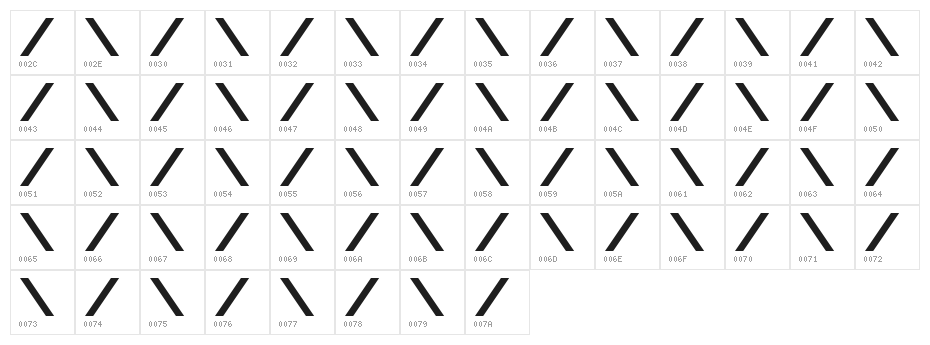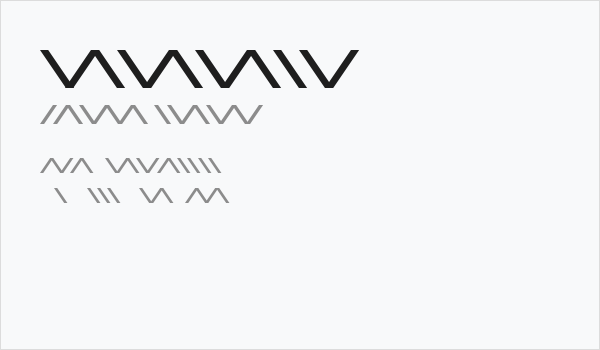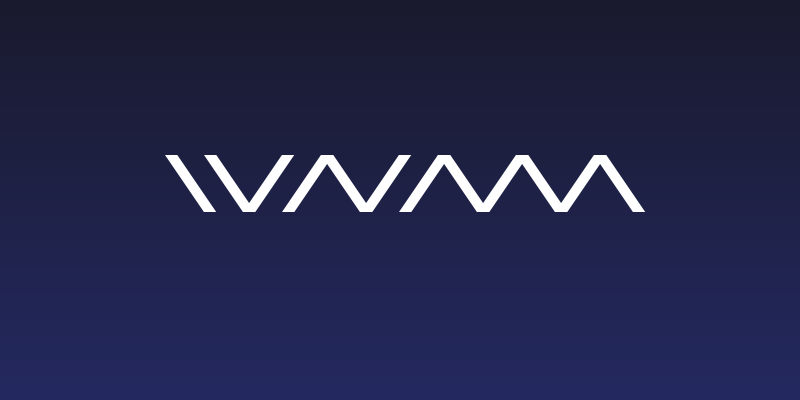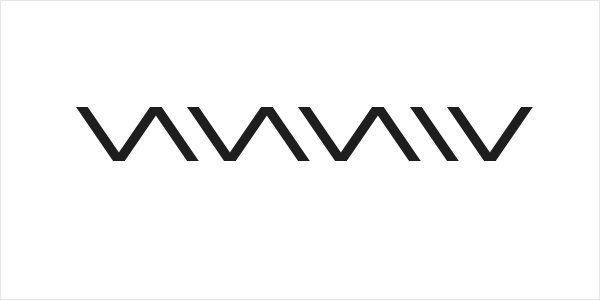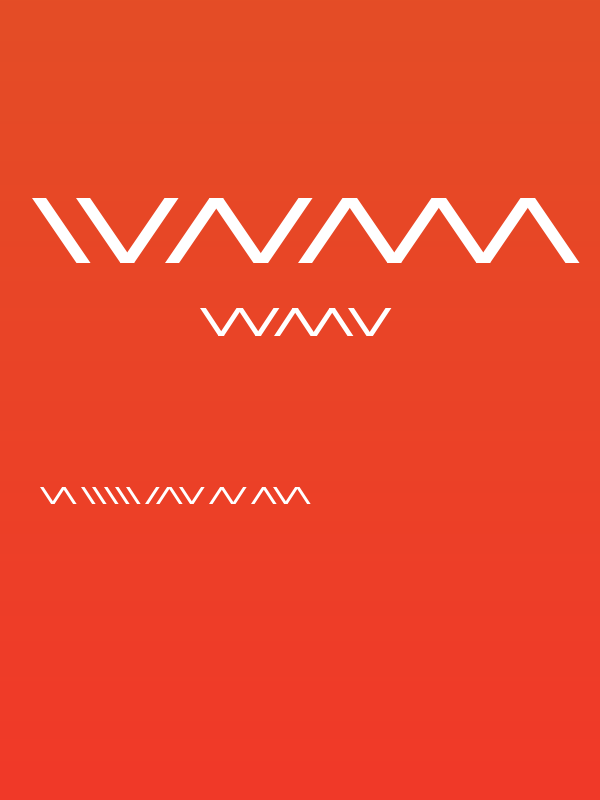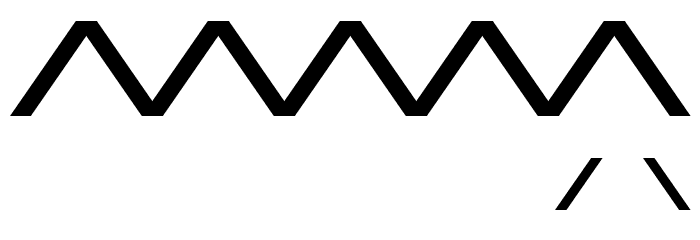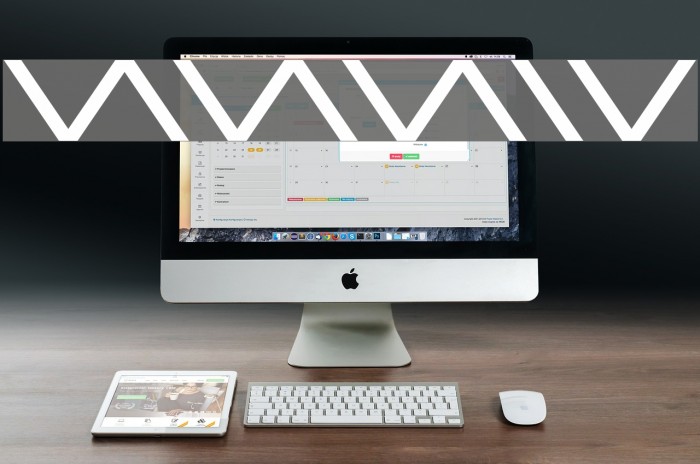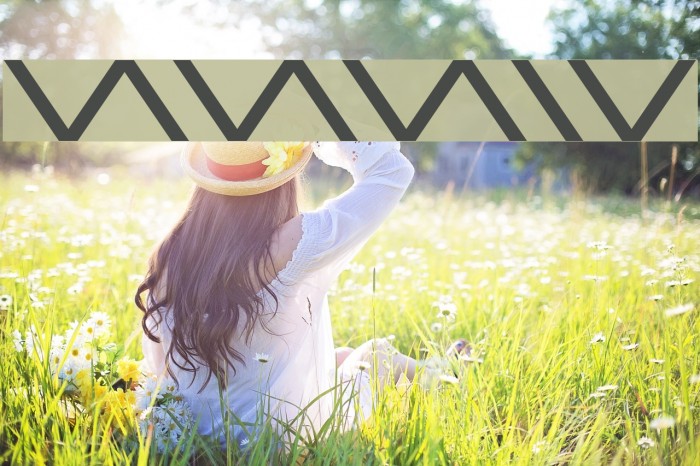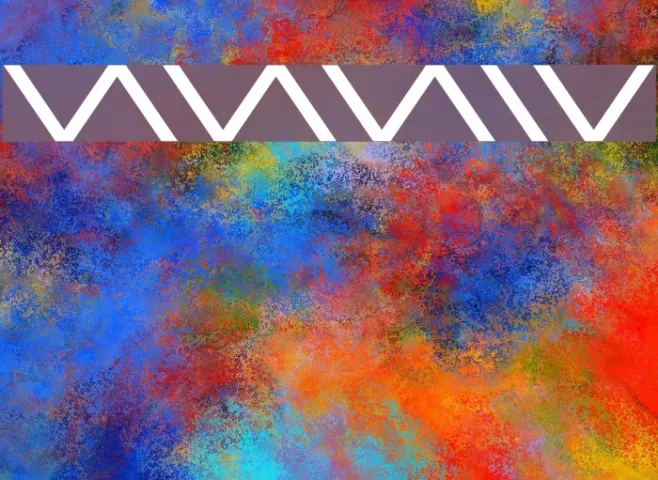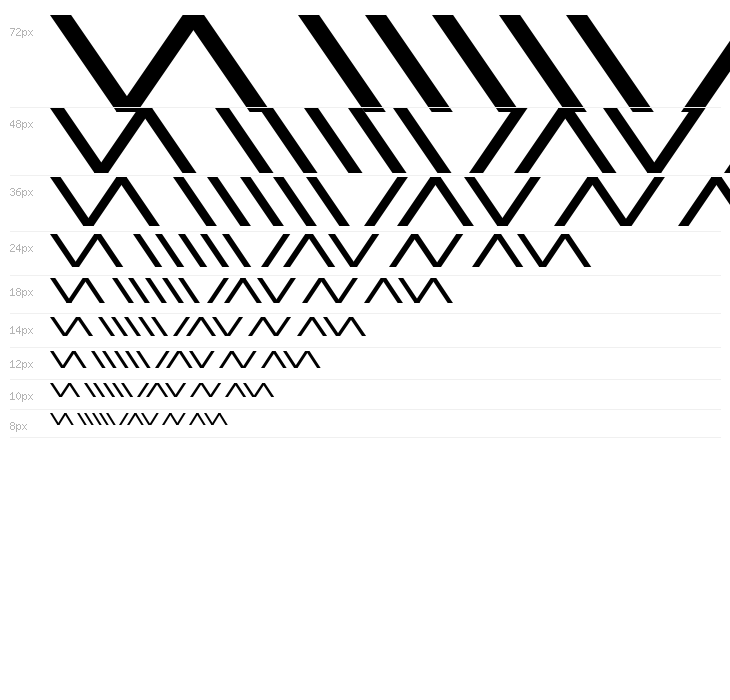
FractionsFat Font
| Caso d'uso | Decorative elements, backgrounds, textiles. |
| Progetti proposti | Ideal for use in textile design, wallpapers, or as a background in graphic design projects. |